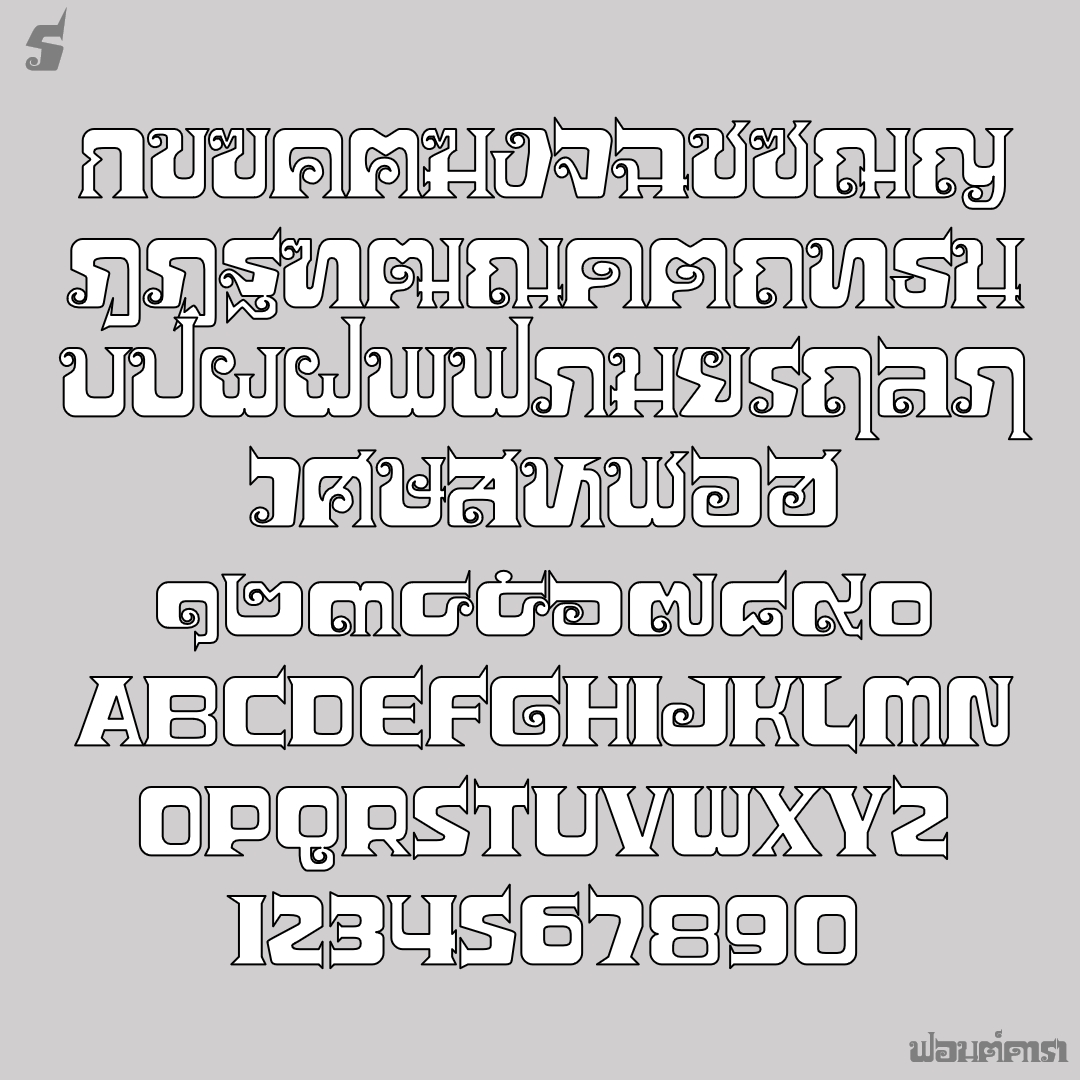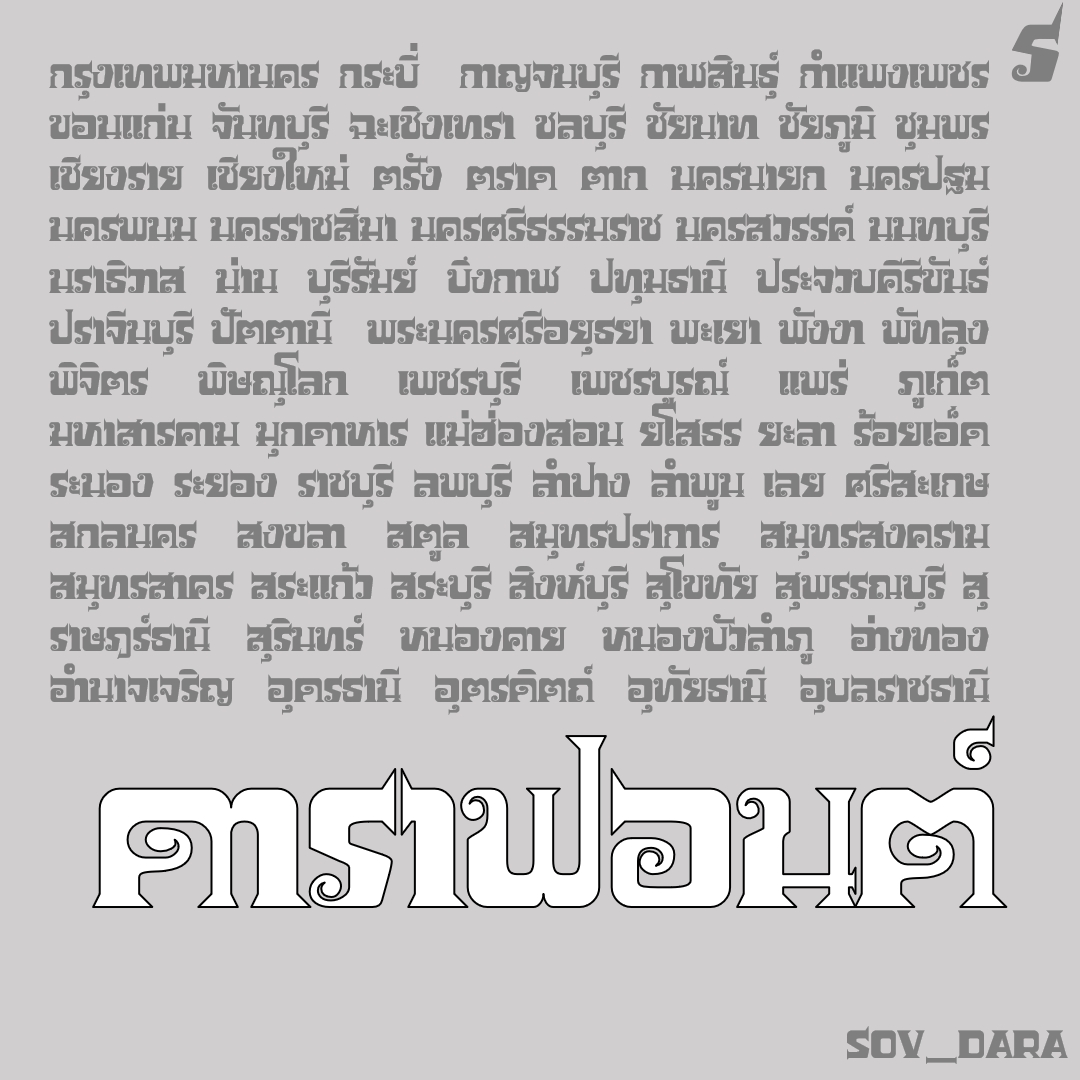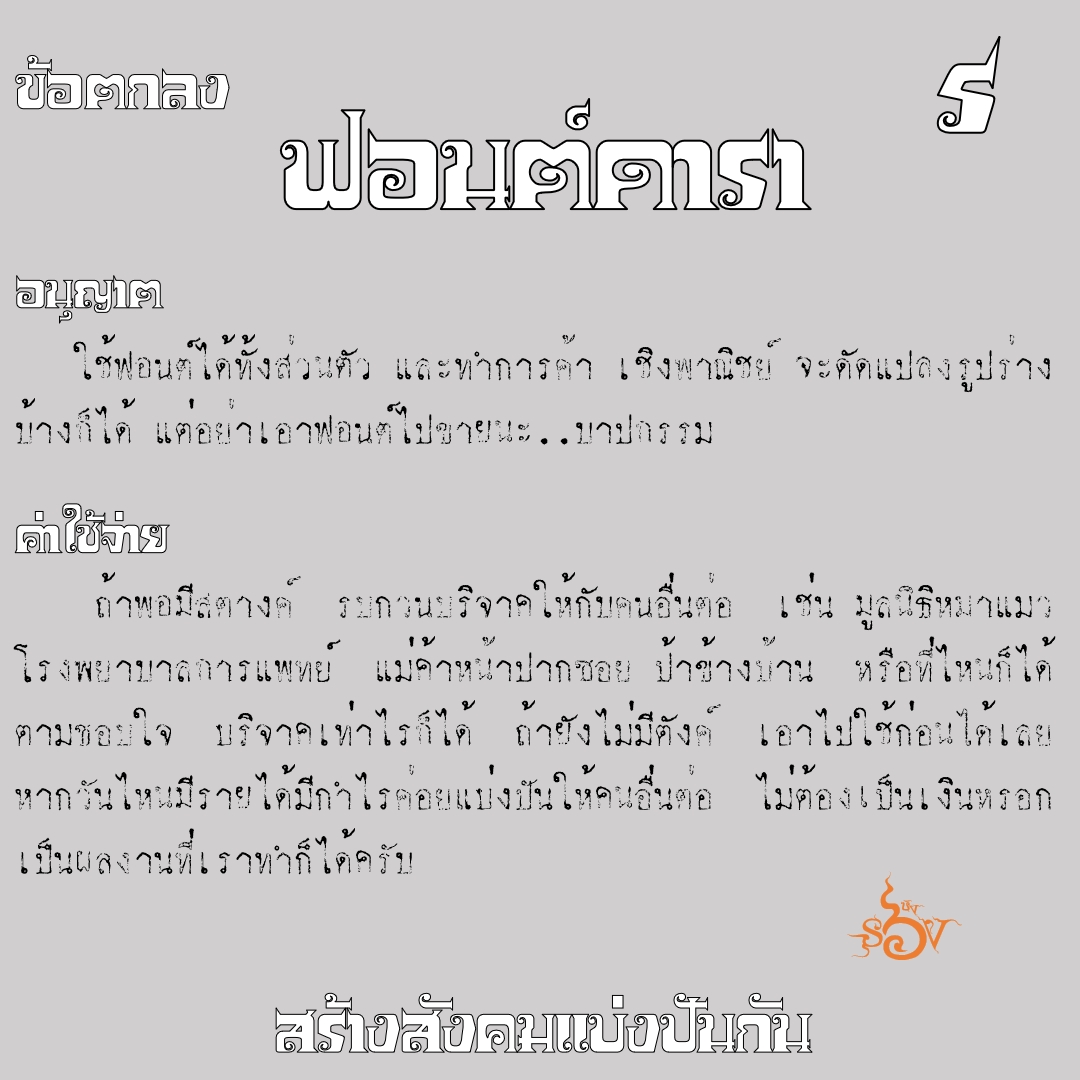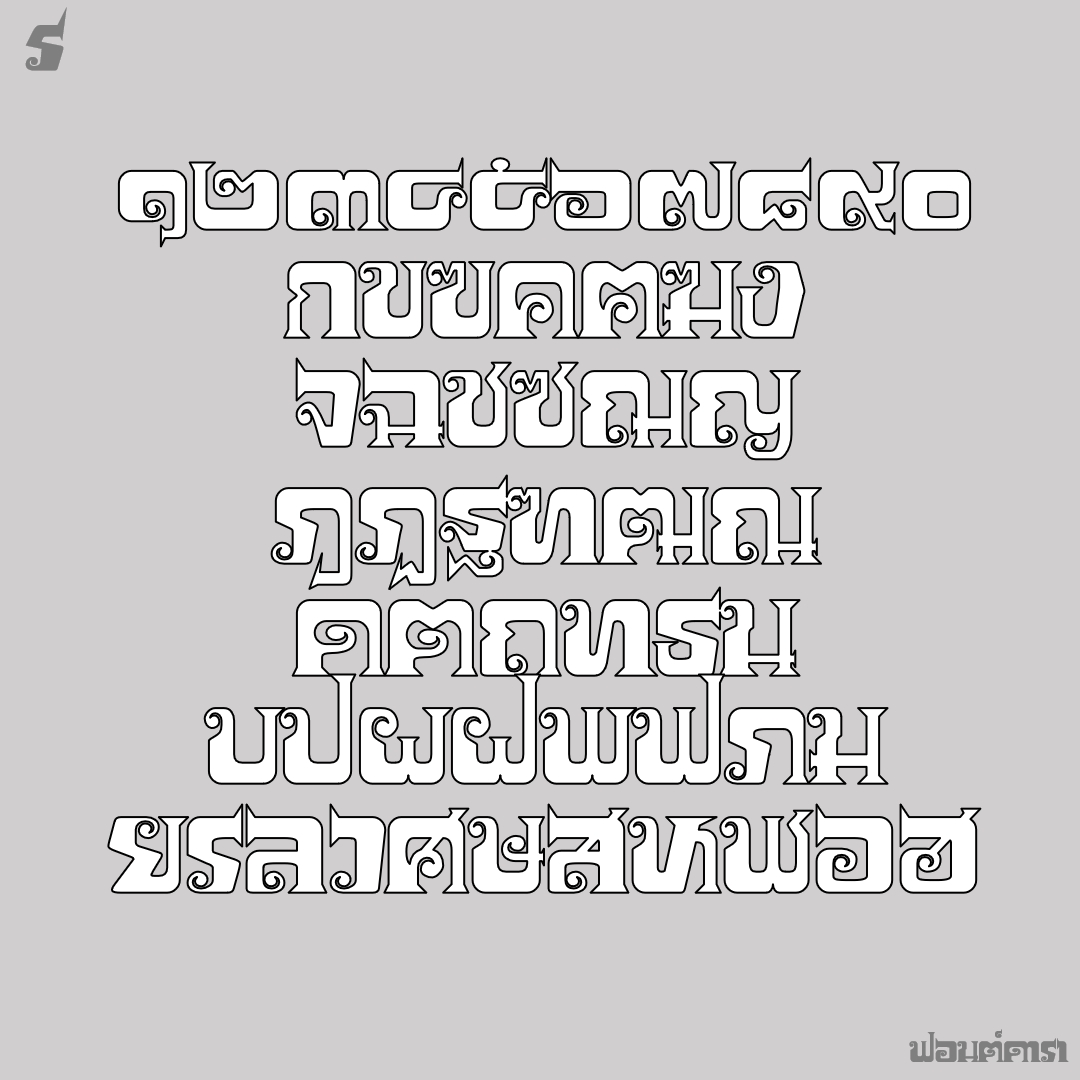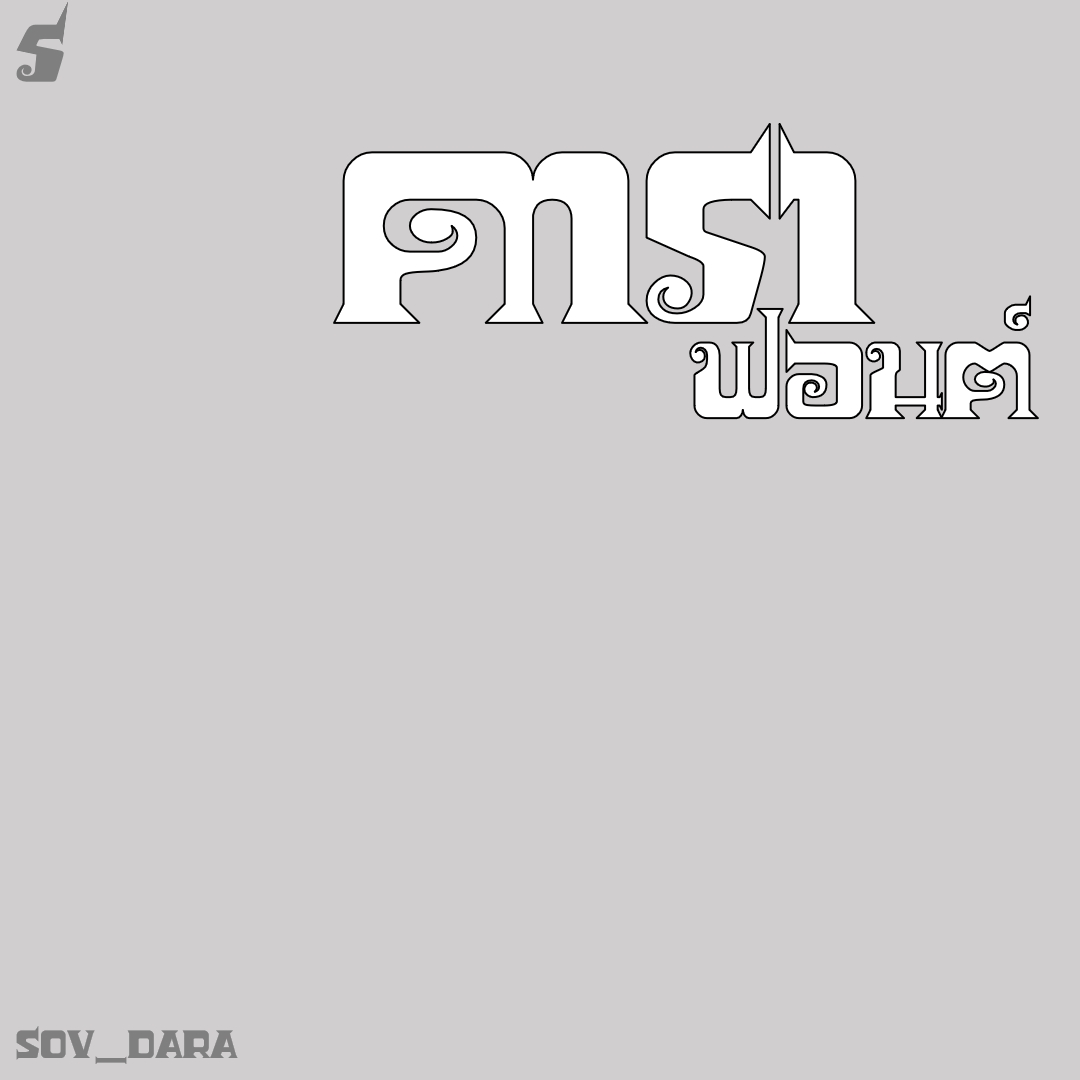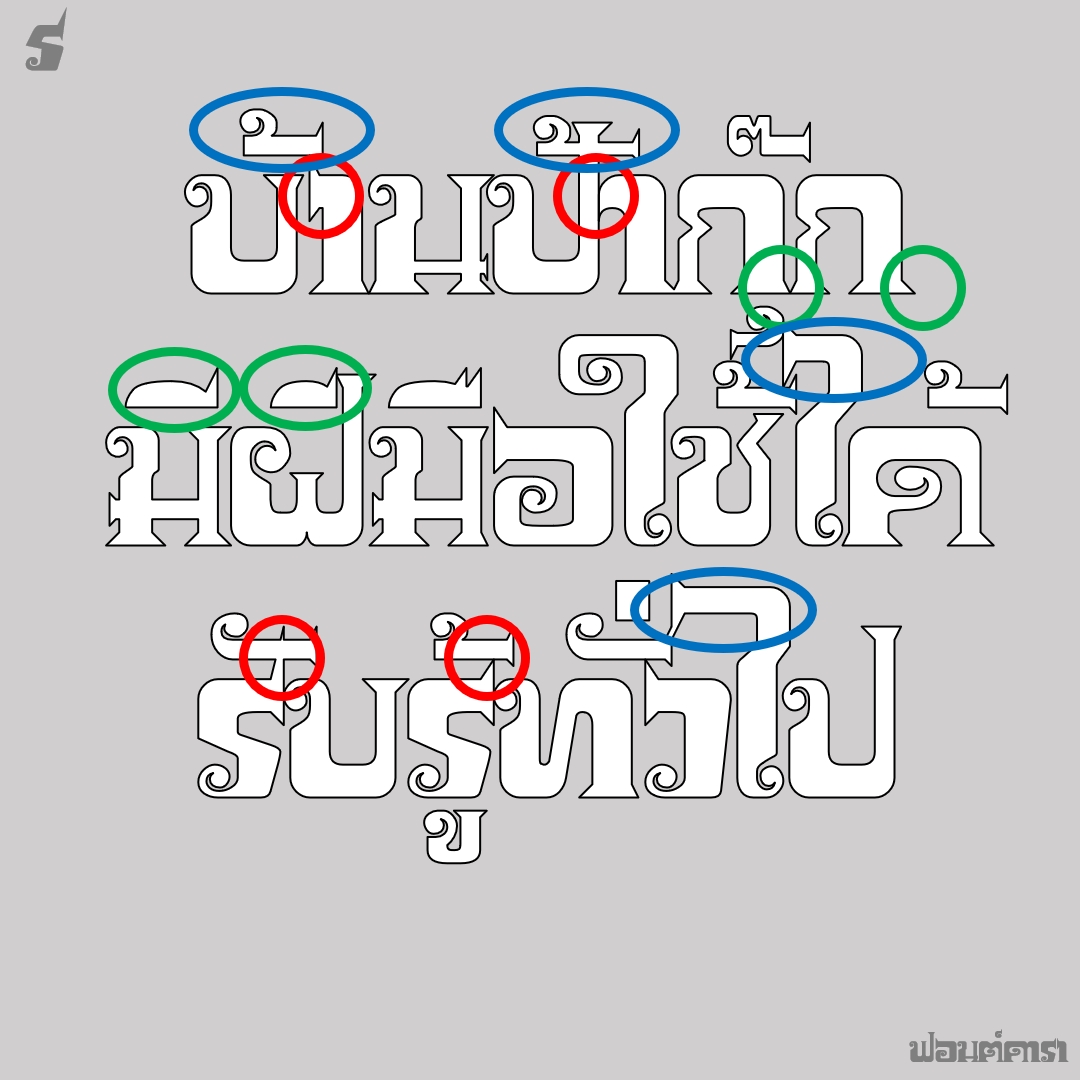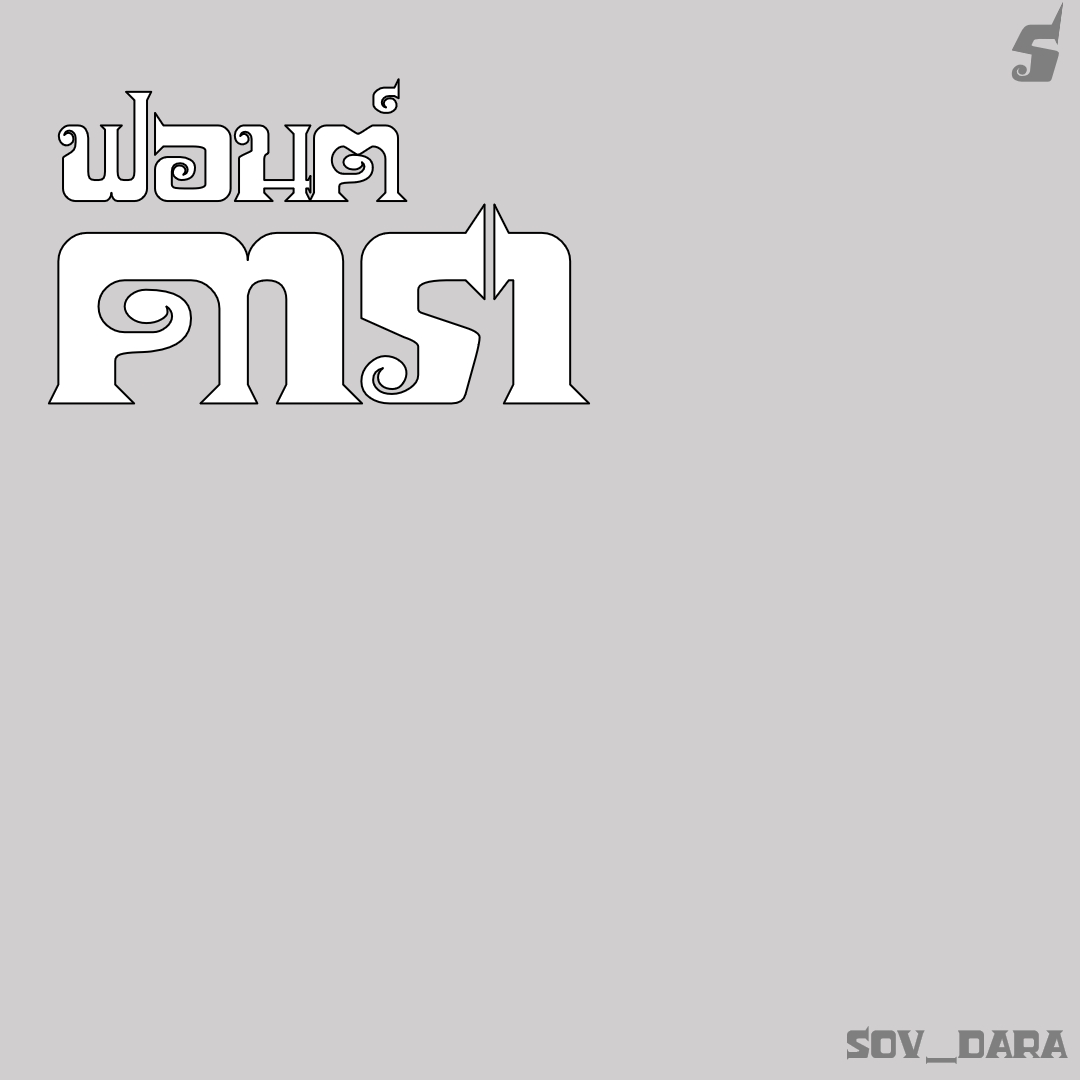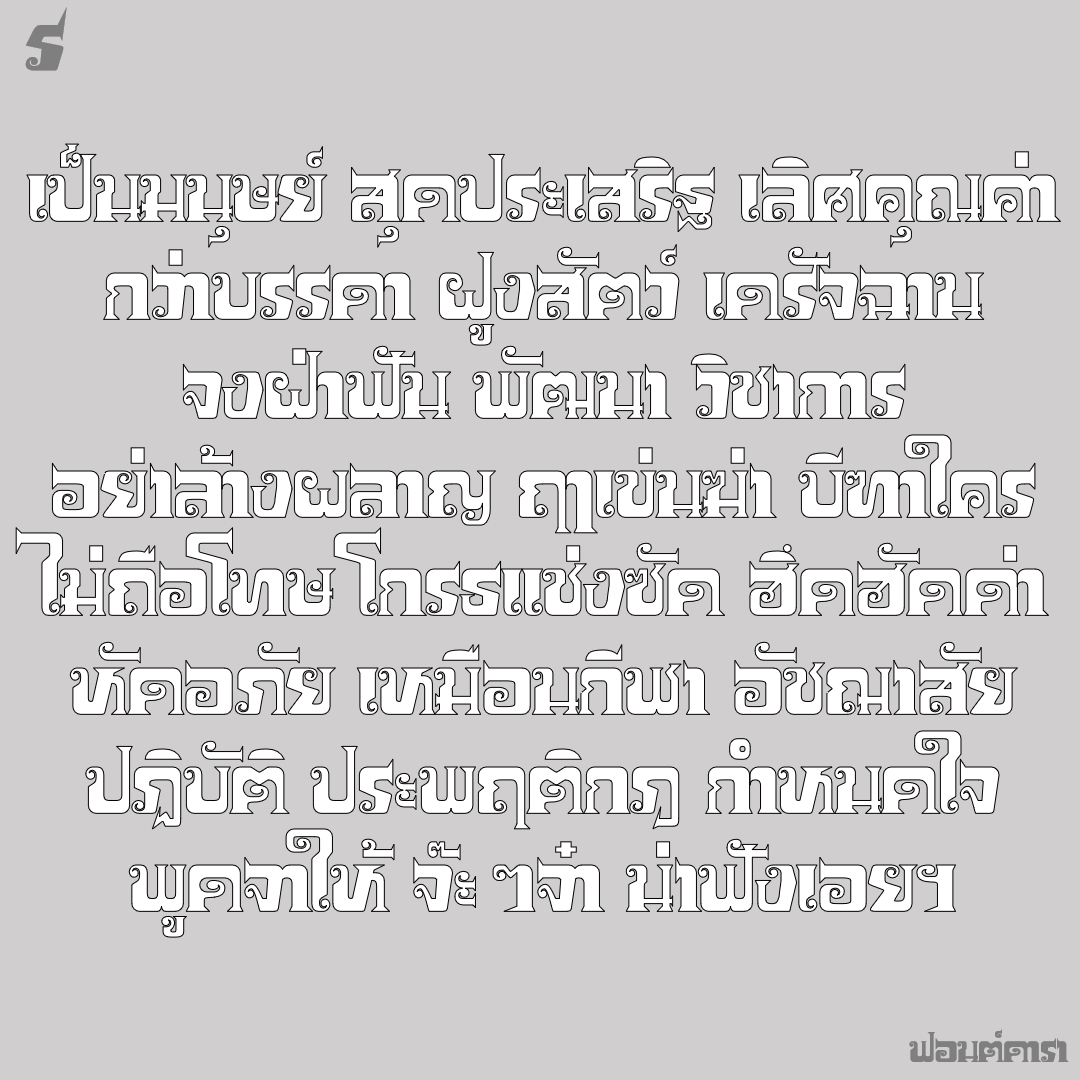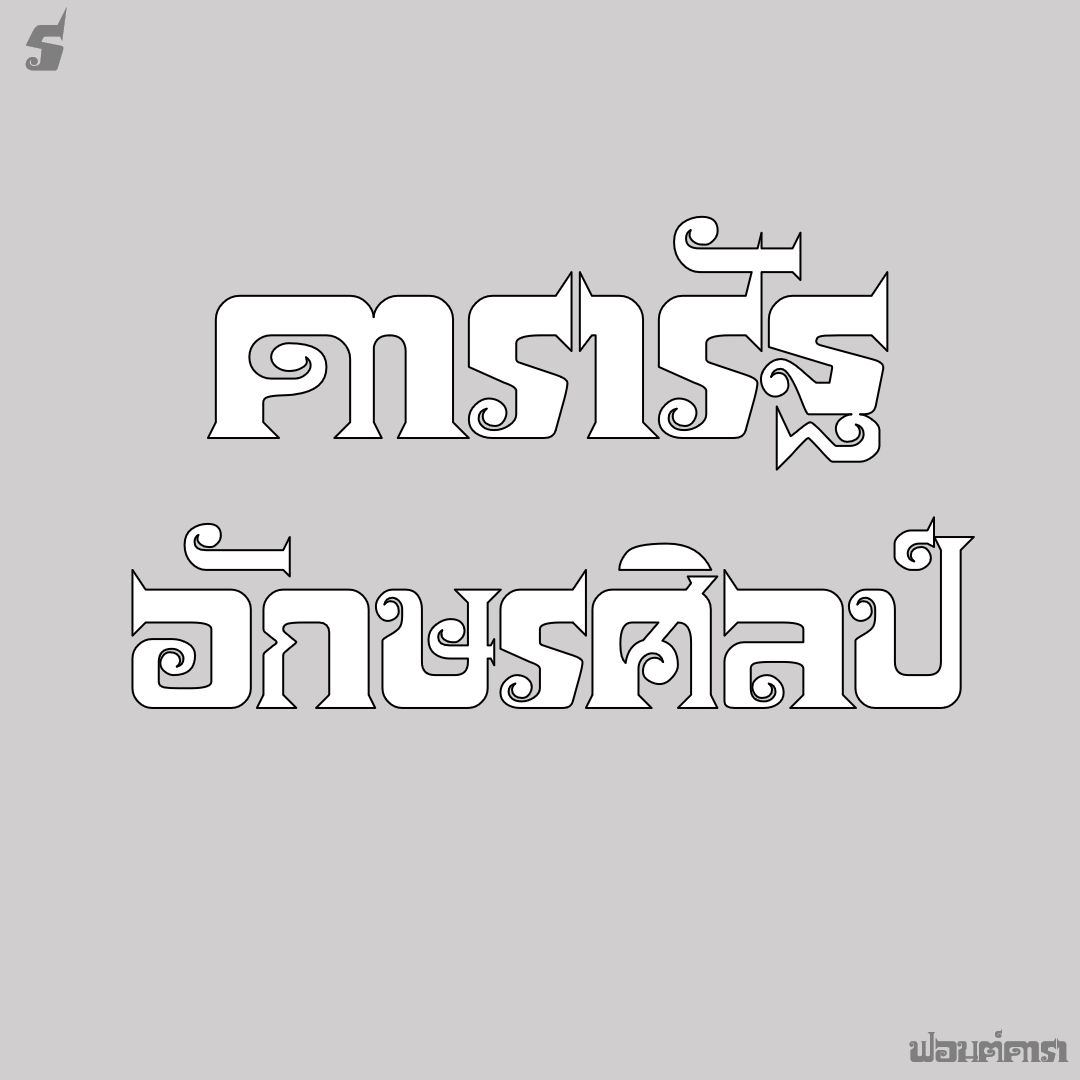
ฟอนต์ ดารา
ต้นทางจากนิตยสาร "ดารารัฐ" สะดุดที่สระอา.. ก็เลยหยิบมาทำเป็นฟอนต์
ชื่อฟอนต์ : ดารา
ต้นทางจากนิตยสาร "ดารารัฐ" สะดุดที่สระอา.. ก็เลยหยิบมาทำเป็นฟอนต์
คุณสมบัติ..เล็กๆ
แอบทำความหลากหลายของอักษรนิดหน่อย เช่น
1. สระอา หน้าตาเปลี่ยน
2. ไม้โท สระอี ยาวไม่เท่ากัน
3. ฐานแหลม ยืดหด
4. สระไอ หดหัว
5. ปลาย ร.เรือ แหลมเปี๊ยว